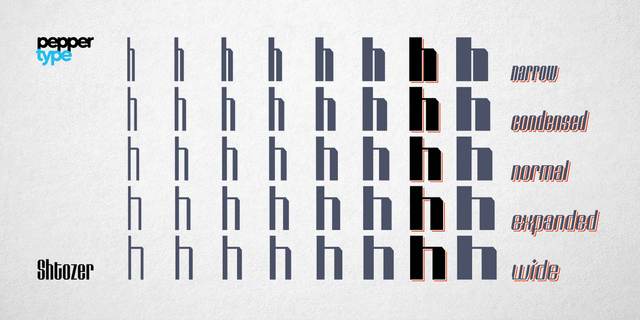
Высококонтрастная версия шрифта Штозер. Акцидентный шрифт в стиле ретро, созданный по мотивам 1960-х и 1970-х годов, дополнительно вдохновленный кириллической вязью. Он поставляется в 8 весах, с 5 вариациями ширины для каждого, все сопровождаются соответствующими наклонными версиями – в общей сложности 80 начертаний. Shtozer – шрифтовое семейство с широким языковым охватом, включающее кириллицу. Гарнитура также содержит множество функций OpenType и альтернативных символов для оживления набора. Шрифт разработал Олег Лищук в 2020 году.
Ассоциации c начертанием Shtozer 700 NormalКачества и характер:
электронный, молодежный, ровный, точный, автоматический, техногенный, твердый, статичный, резкий, четкий, устойчивый, стабильный, прямоугольный, городской, машинный, инженерный, урбанистический, чертежный, надежный, уверенный, стальной, космический, убедительный, серьезный, сильный, индустриальный, железный, мужественный, военный, промышленный, ломаный, угловатый, заметный, броский, активный, рабочий, кинематографичный, граненый, громкий, тесный, черный, мощный, тяжелый, оригинальный, брутальный, толстый, настойчивый, массивный, увесистый, громоздкий, характерный, яркий, крутой, грубый, урбанистичный
конструктор, станок, чертеж, инженер, урбанистика, электроника, машина, инструмент, робот, игра, космос, техника, автомат, шутер, андроид, железо, лего, игрушка, кубики, город, архитектура, реклама, тренажеры, стикер, наклейка, компьютерная игра Стилистика: